34 meilleures polices de CV 2023 (gratuites et premium)
Publié: 2023-08-24Êtes-vous un graphiste qui cherche à faire passer vos projets au niveau supérieur ? Voulez-vous vous assurer que votre CV se démarque des autres ? Alors vous êtes au bon endroit !
Dans cet article de blog, nous discuterons des 34 meilleures polices de CV que tout graphiste devrait envisager d'utiliser. Que vous débutiez ou que vous ayez des années d'expérience à votre actif, une police peut faire toute la différence dans la façon dont votre travail est perçu.
Maintenant, vous vous demandez peut-être pourquoi les polices sont si importantes lorsqu'il s'agit de CV. Eh bien, la vérité est que la police que vous choisissez peut en dire long sur vous en tant que designer. Il peut transmettre votre niveau de professionnalisme, de créativité et d’attention aux détails.
En fait, des études ont montré que certaines polices peuvent même avoir un impact sur la rapidité avec laquelle les responsables du recrutement et les recruteurs lisent votre CV.
Dans cet article, nous explorerons une variété de polices qui sont non seulement visuellement attrayantes, mais également parfaitement adaptées aux CV.
Nous aborderons les caractéristiques et fonctionnalités spécifiques de chaque police et fournirons quelques conseils pratiques sur comment et quand les utiliser. Alors sans plus tarder, commençons et trouvons la police parfaite pour faire briller votre CV !
Meilleures polices de CV Premium
Êtes-vous un graphiste à la recherche de la police parfaite pour rehausser le design de votre projet ? Cherchez pas plus loin! Dans cette section du blog post-Meilleures polices de CV, nous explorons le domaine des polices haut de gamme qui ne manqueront pas d'impressionner.
N'oubliez pas de consulter ces polices soigneusement sélectionnées ci-dessous pour un délicieux regain de créativité dans la conception de votre CV. Poursuivez votre lecture pour découvrir la police qui fera passer vos créations de bonnes à extraordinaires !
Stickler
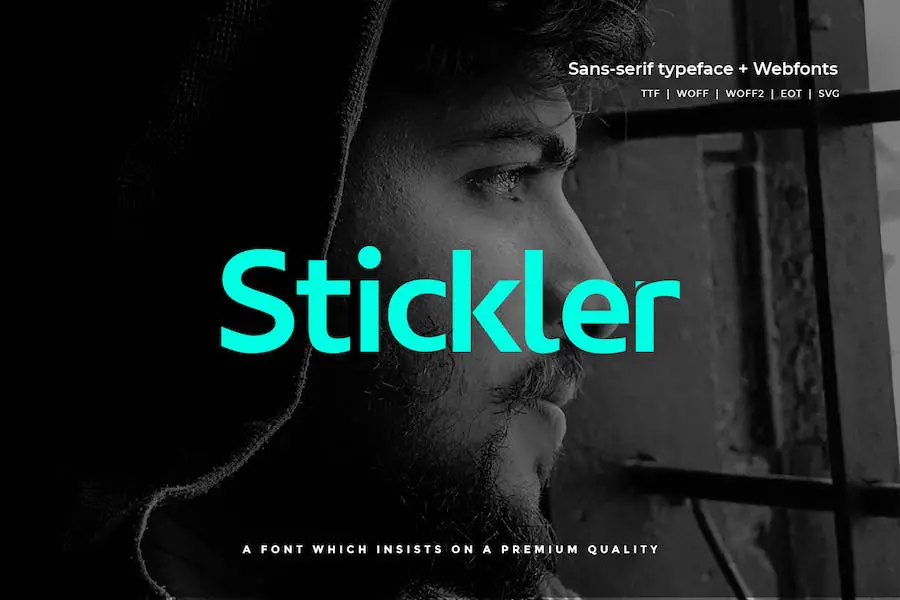
Stickler est une police Sans Serif moderne et minimaliste, parfaite pour les conceptions typographiques créatives et classiques. Avec son apparence épurée et élégante, Stickler peut améliorer l’esthétique globale de n’importe quel projet.
Stickler maintient sans effort un sentiment de minimalisme, ce qui en fait un choix idéal pour ceux qui recherchent un look élégant et contemporain pour leurs projets de conception.
Yarelli
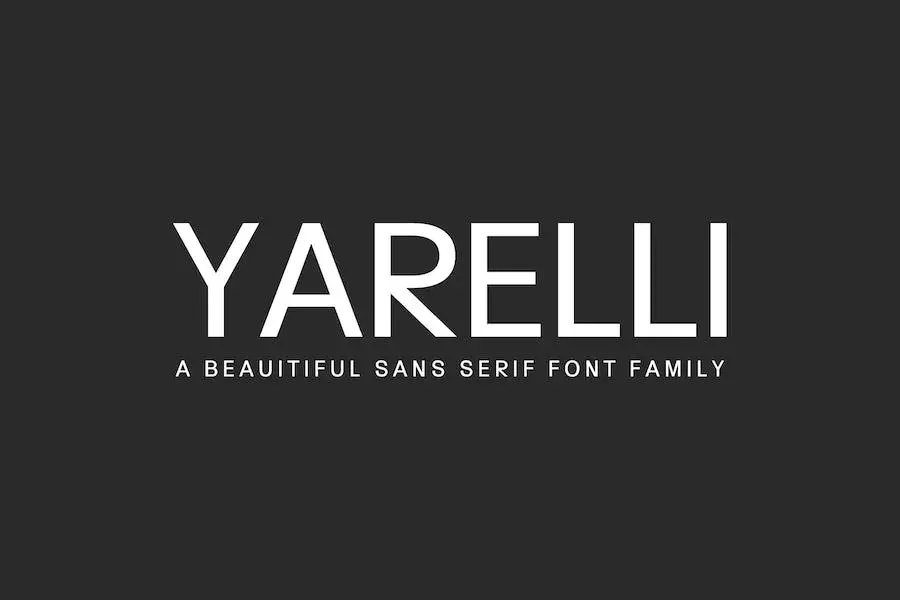
Yarelli est une police sans empattement créative et simple qui ajoute une touche étonnante à n'importe quel design. Avec ses 3 poids, il offre polyvalence et flexibilité pour divers projets.
Qu'il s'agisse de magazines, de logos, d'invitations ou de publications sur les réseaux sociaux, Yarelli offre un look élégant et professionnel.
Son application est vaste et comprend des présentations, des affiches, des avis, des titres, des cartes de visite, des mises en page Web, des en-têtes, l'image de marque, les mariages, la conception de produits et la publicité. En bref, Yarelli est la police incontournable pour tous vos besoins de conception professionnels.
Jackyline
Jackylin est une police sans empattement moderne et fantastique créée par Unbranded. Ce style typographique unique est parfait pour ajouter une touche de sophistication à n’importe quel projet.
Avec Jackylin, vous disposerez de tous les outils dont vous avez besoin pour améliorer vos créations et créer un look professionnel et soigné.
Lumière
Lumiera est une police duo sans empattement polyvalente qui ajoute une touche de modernité et de luxe à tout projet de conception. Avec ses styles manuscrits épurés, bruts et doux, cette police est parfaite pour créer un look luxueux ou classique.
Que vous conceviez une couverture de magazine, un titre de site Web, une invitation, un logo, une carte de visite ou même un CV, Lumiera est là pour vous.
Privity est une police Sans Serif moderne et minimale, parfaite pour les conceptions typographiques créatives et classiques. Avec ses lignes épurées et sa simplicité, il peut rehausser le design de n’importe quel projet.